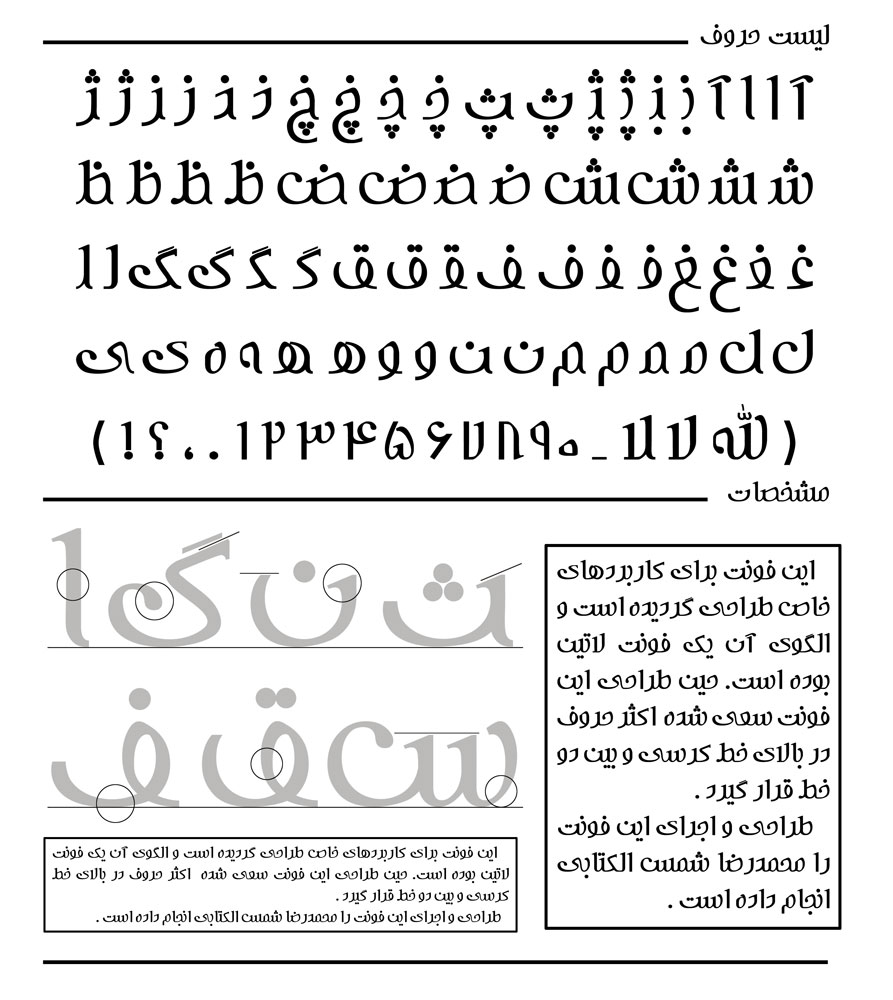
فونت زیبای شمس
فونت شمس / طراح : محمدرضا شمس الکتابی
فونت زیبای شمس یکی از فونت‌های زیبای فارسی است . الگوی فونت شمس یک فونت لاتین بوده است . این فونت توسط محمدرضا شمس الکتابی در سال ۱۳۹۰ طراحی شده است . امیدوارم مورد پسند شما ، عزیزان قرار گیرد و آن را دانلود نمایید . شما می‌توانید در طراحی پوسترها ، تراکت‌ها و … از این فونت زیبا استفاده نمایید و با کمی خلاقیت ، بهترین اثر را خلق کنید .
فونت شمس / Shams Font
پیش نمایشی از فونت زیبای شمس